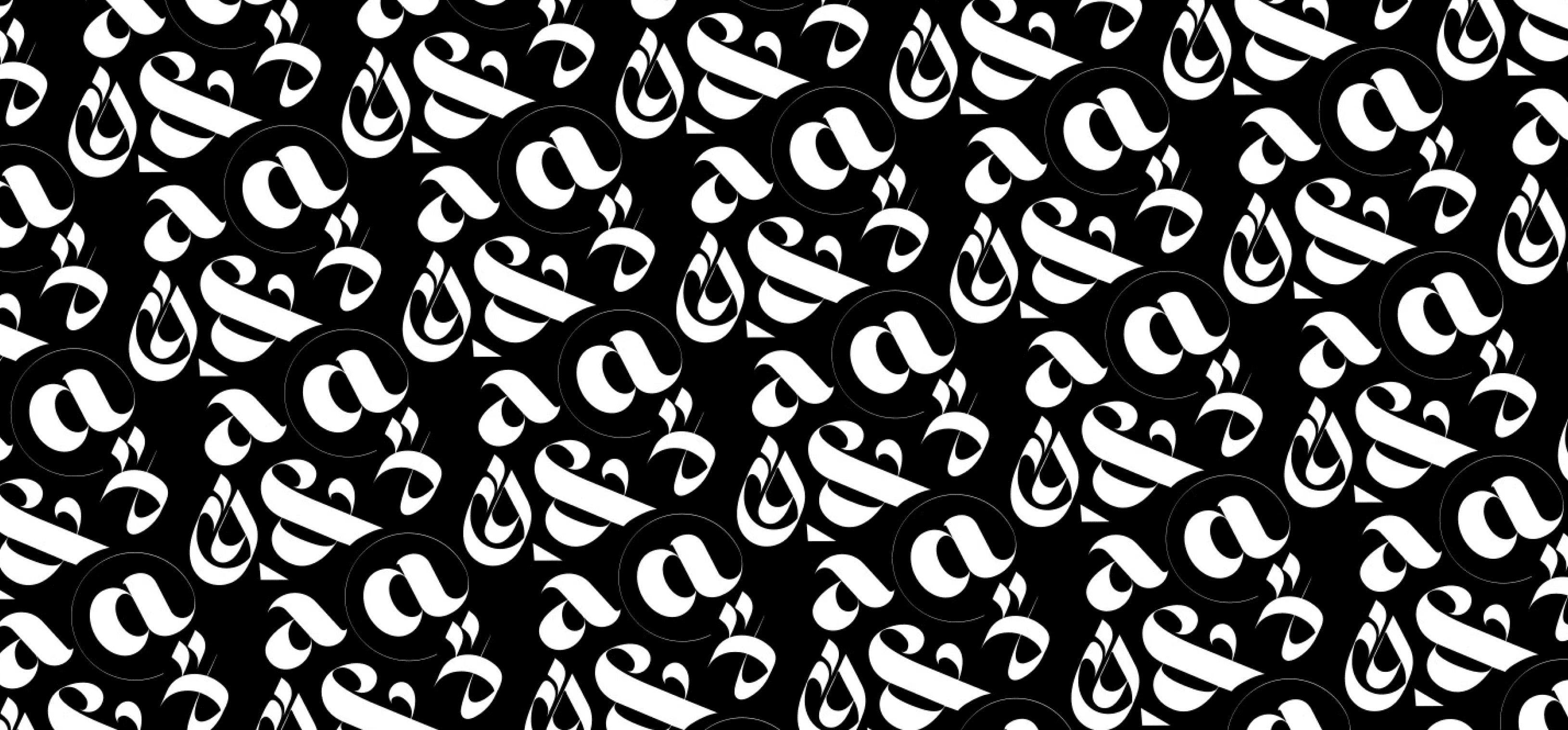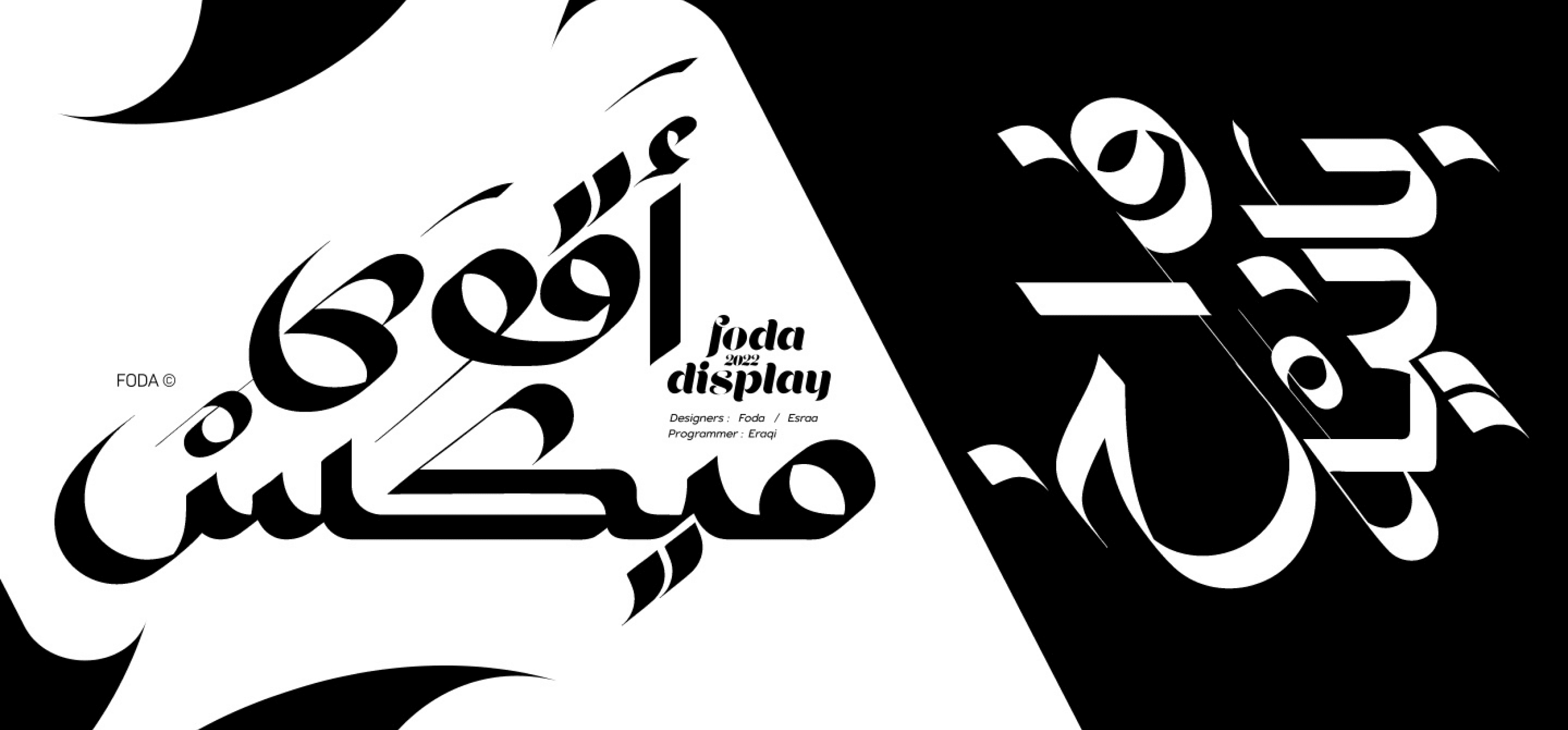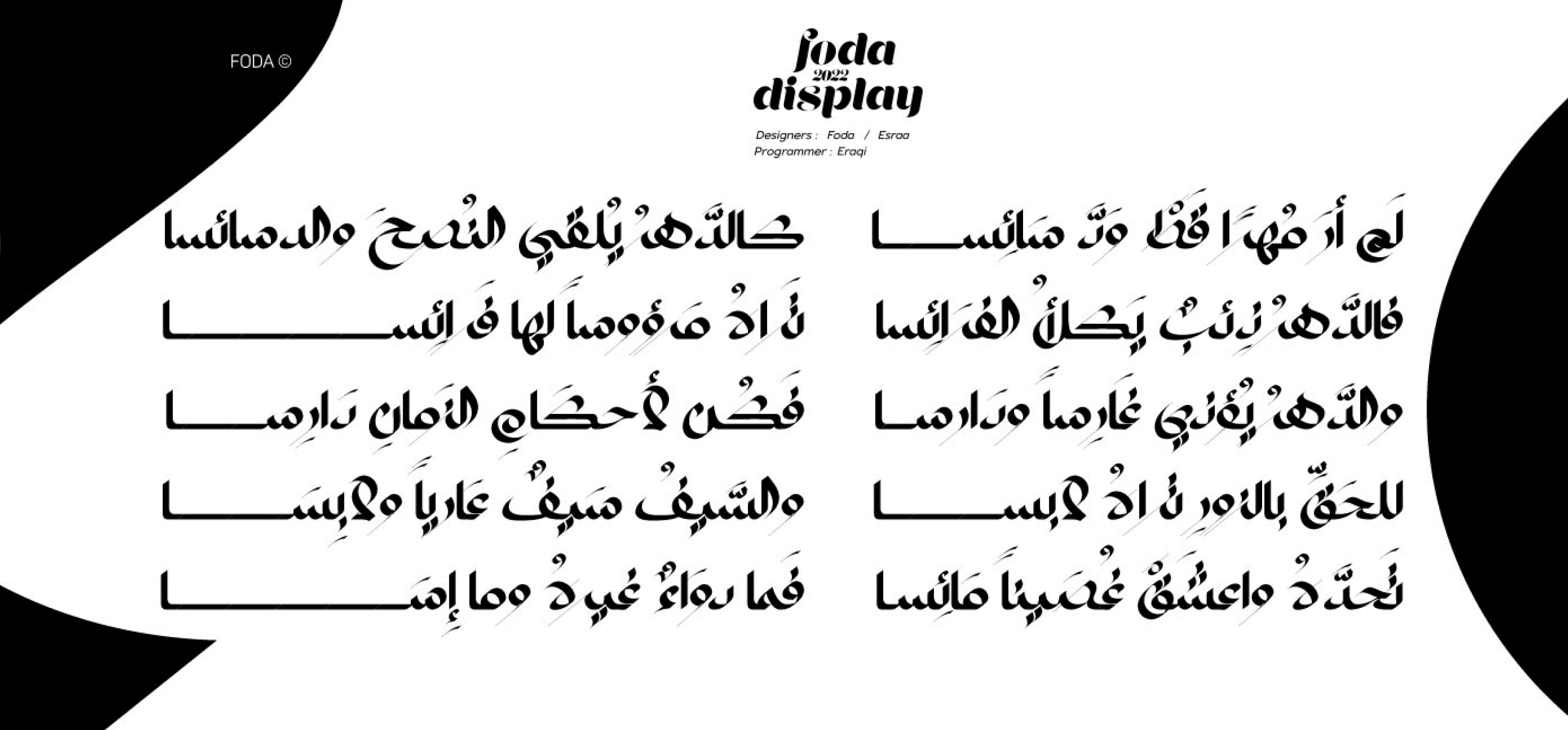
خط العرض Foda Display للّاتيني والعربي هو خط خطّي عصري ويُعد من الإبداعات الجديدة لمصنع FoDa.
يناسب الاستخدام في العلامات التجارية، الشعارات، التعبئة والتغليف، الإعلانات، تصميمات وسائل التواصل الاجتماعي، الملصقات، بطاقات الدعوة لحفلات الزفاف، وأكثر...
يتوفر Foda Display بوزنين: عادي ومائل، ويحتوي على مجموعة أساسية تزيد عن 750 رمزًا تدعم العديد من ميزات OTF مثل:
دعم متعدد اللغات للعديد من الخطوط اللاتينية والعربية.